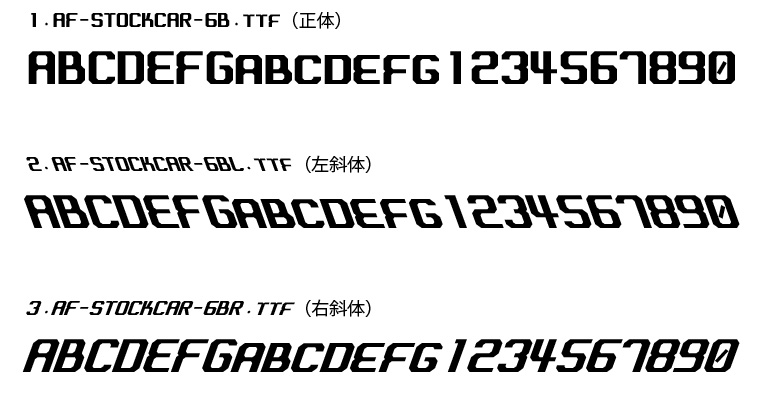
本商品は下記3書体のセットです。
AF-STOCKCAR-6B.ttf(正体)
AF-STOCKCAR-6BL.ttf(左斜体)
AF-STOCKCAR-6BR.ttf(右斜体)
※プレビューフォントは「AF-STOCKCAR-6B.ttf(正体)」です。
アメリカのストックカーレーシングで使われるレースカー側面に貼られる数字や文字を模した1Byte欧文デザインフォントです。
AP機能の関わらず左右斜体が利用できる便利なセットです。